งานด่วนไฟไหม้เกิดขึ้นจนเป็นเรื่องปกติ การสร้างปาฏิหาริย์ในทุก ๆ งานในเวลาที่จำกัด มันอาจจะเรียกว่าปาฏิหาริย์ไม่ได้อีกต่อไป การที่จะเกิดปาฏิหาริย์ได้นั้น มันต้องเกิดขึ้นเป็นบางครั้งบางคราว เพราะว่าปาฏิหาริย์มันไม่ควรจะเกิดขึ้นในทุก ๆ วันต่างหาก
ในเมื่องานมันเร่งคนมันรีบ อะไรที่มีติดเครื่องมาให้ก็ลองใช้ให้มันให้คุ้มหน่อย ฟอนต์ที่ติดกับระบบปฏิบัติการมานั้นมันก็ไม่ได้แย่เสมอไป ลองเปิดใจใช้ดูก่อนมันอาจจะช่วยให้ปาฏิหาริย์มีจริงในทุก ๆ ครั้งก็ได้
วันนี้เราจะหยิบฟอนต์ที่ติดมาในเครื่องของ Mac Os มาแนะนำกัน 5 แบบ อีกทั้งเรายังได้สอบถามนักออกแบบจำนวน 3 คนที่โลดแล่นอยู่ในวงการออกแบบ ว่าพวกเขาเลือกใช้ฟอนต์อะไรกันเมื่อจำเป็นต้องทำงานที่รีบเร่ง
Helvetica
ฟอนต์ยอดฮิต ที่แบรนด์ใหญ่ ๆ ต่างก็เคยผ่านมาใช้ฟอนต์ตระกูลนี้กันมาแล้ว ปัจจุบันก็ยังคงใช้กันอย่างแพร่หลาย
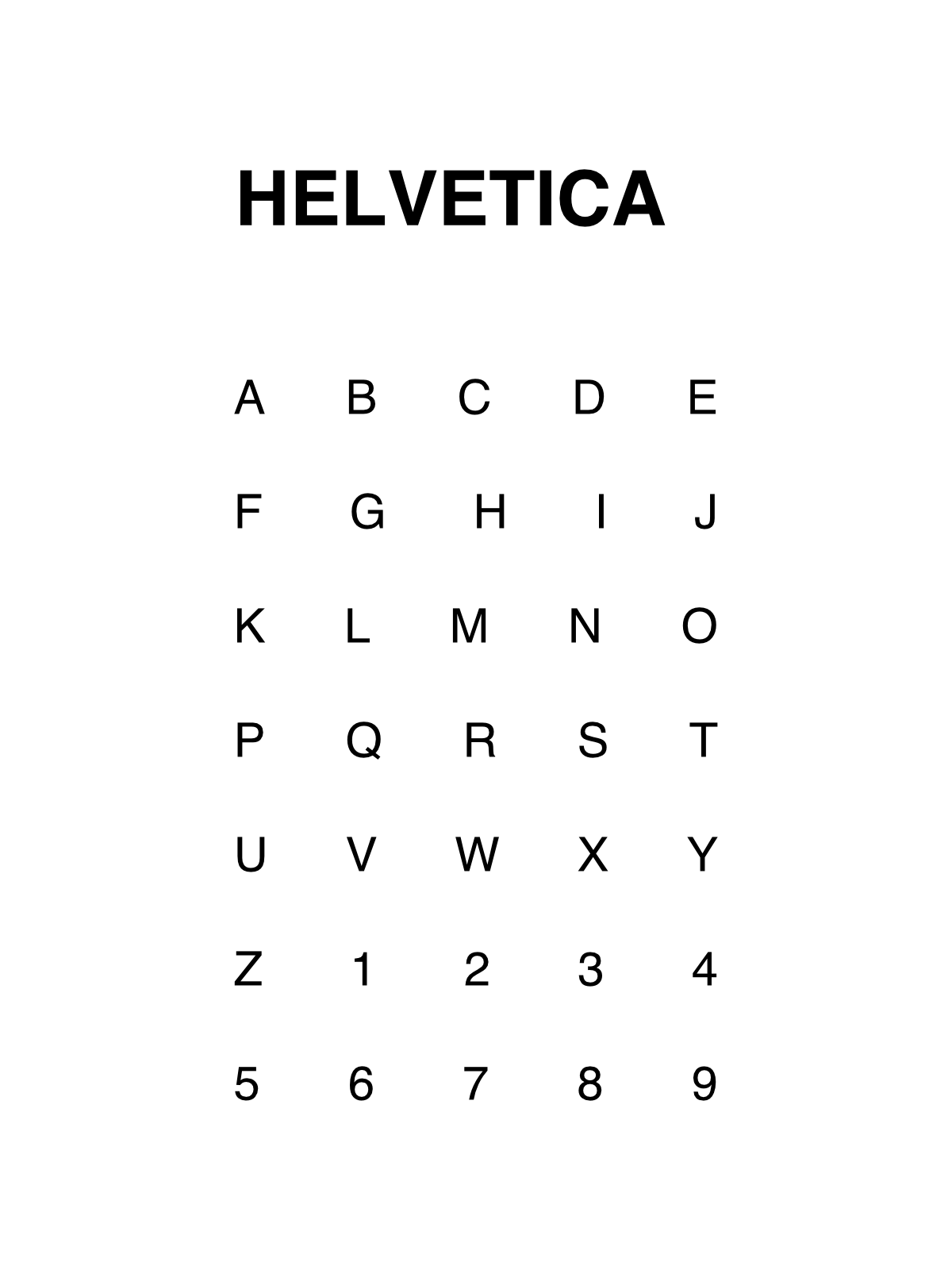
Impact
เป็นอีกหนึ่งฟอนต์ยอดนิยม เริ่มต้นพบเห็นใน Microsoft Windows ตั้งแต่ Windows 98 จนถึงปัจจุบันมันก็ยังไม่มีวันเชย
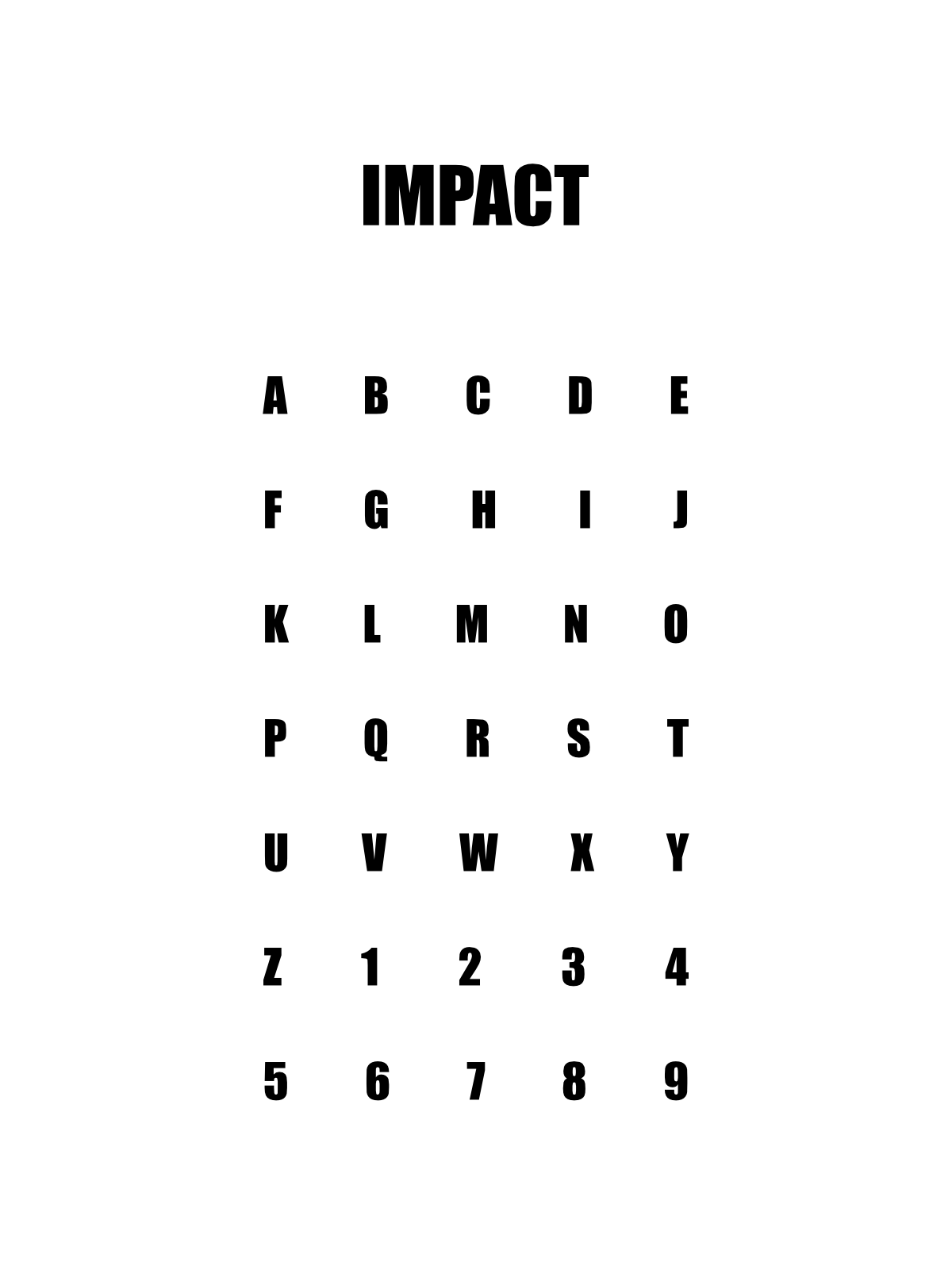
Arial unicode ms
ฟอนต์จากตระกูล Arial ที่มีการใช้กันเป็นมาตรฐานในอุตสาหกรรมเว็บไซต์ Arial unicode ms ส่วนใหญ่จะใช้เกี่ยวกับการเข้ารหัสภาษาคอมพิวเตอร์ ไม่แน่ใจในข้อมูลนัก ถือว่าเป็นฟอนต์ที่เรียบง่ายเหมาะกับการจัดวางในชุดตัวอักษรที่เยอะ
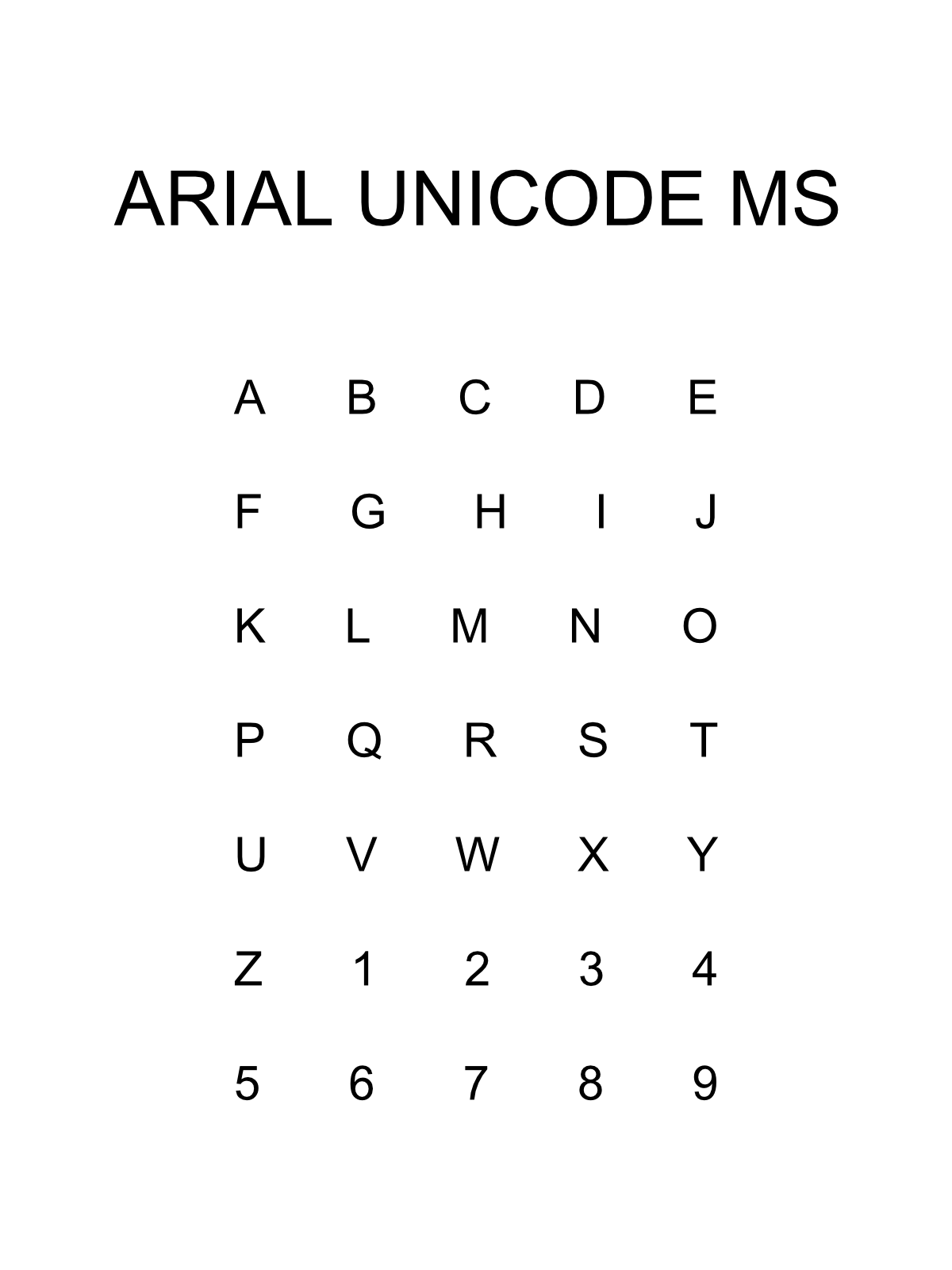
Baskerville
ถือกำเนิดช่วงปี 1750 ฟอนต์ที่มอบความรู้สึกจริงจัง คมชัด เป็นทางการ ส่วนมากถูกใช้กับวงการธุรกิจหรือสื่อหนังสือพิมพ์ ส่วนตัวเราเอาไปใช้กับบรีฟที่บอกว่า ขอหรู ๆ อยากดูแพง ส่วนใหญ่ได้ผล
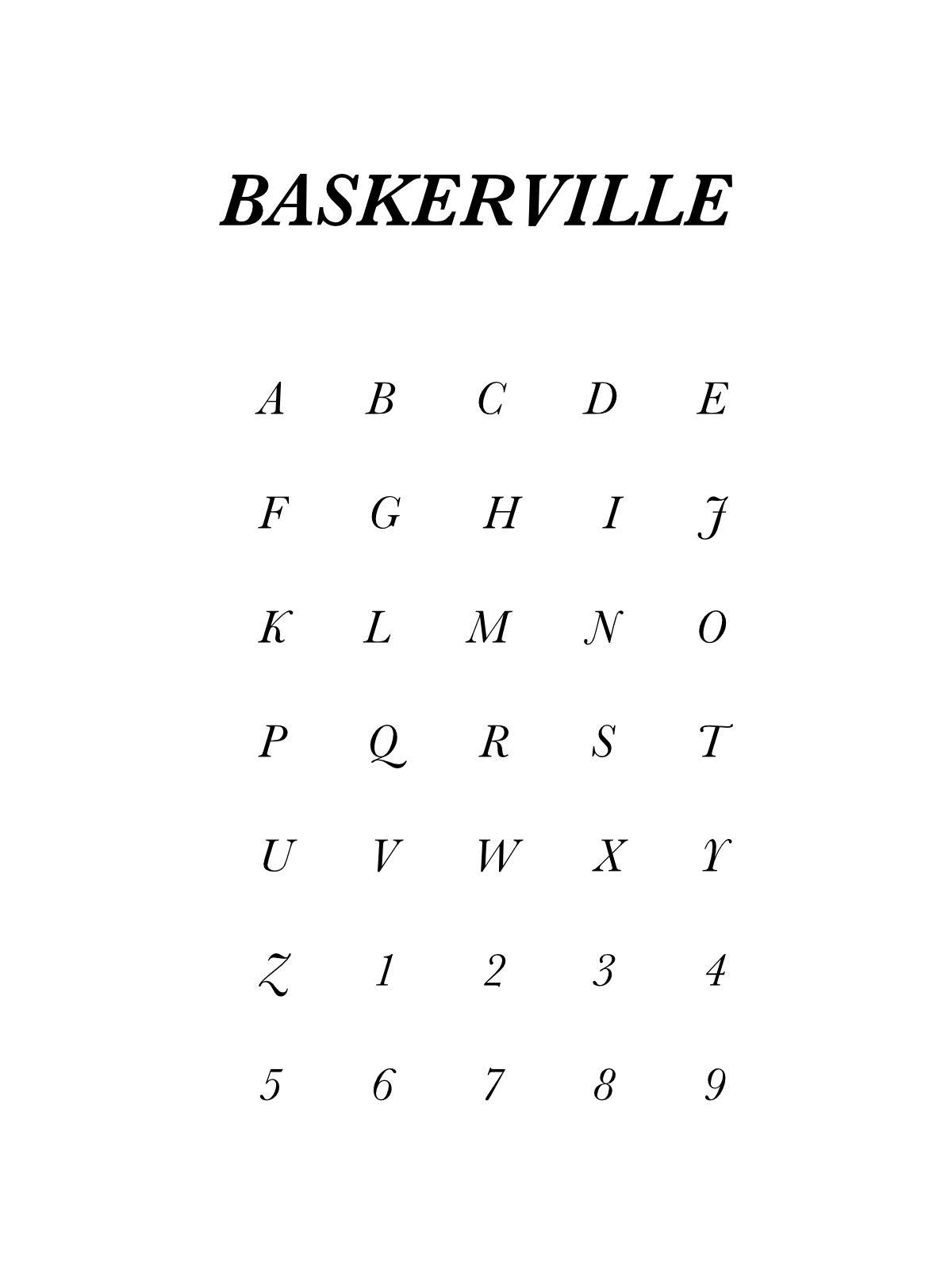
DIN alternate
หาข้อมูลไม่เจอมากนัก แต่เป็นฟอนต์ที่ชอบมากอีก 1 ตัวที่ติดมาในเครื่อง มันถูกปล่อยในปี 1995 จาก FontShop ที่เป็นผู้ผลิตฟอนต์รายใหญ่ในวงการ
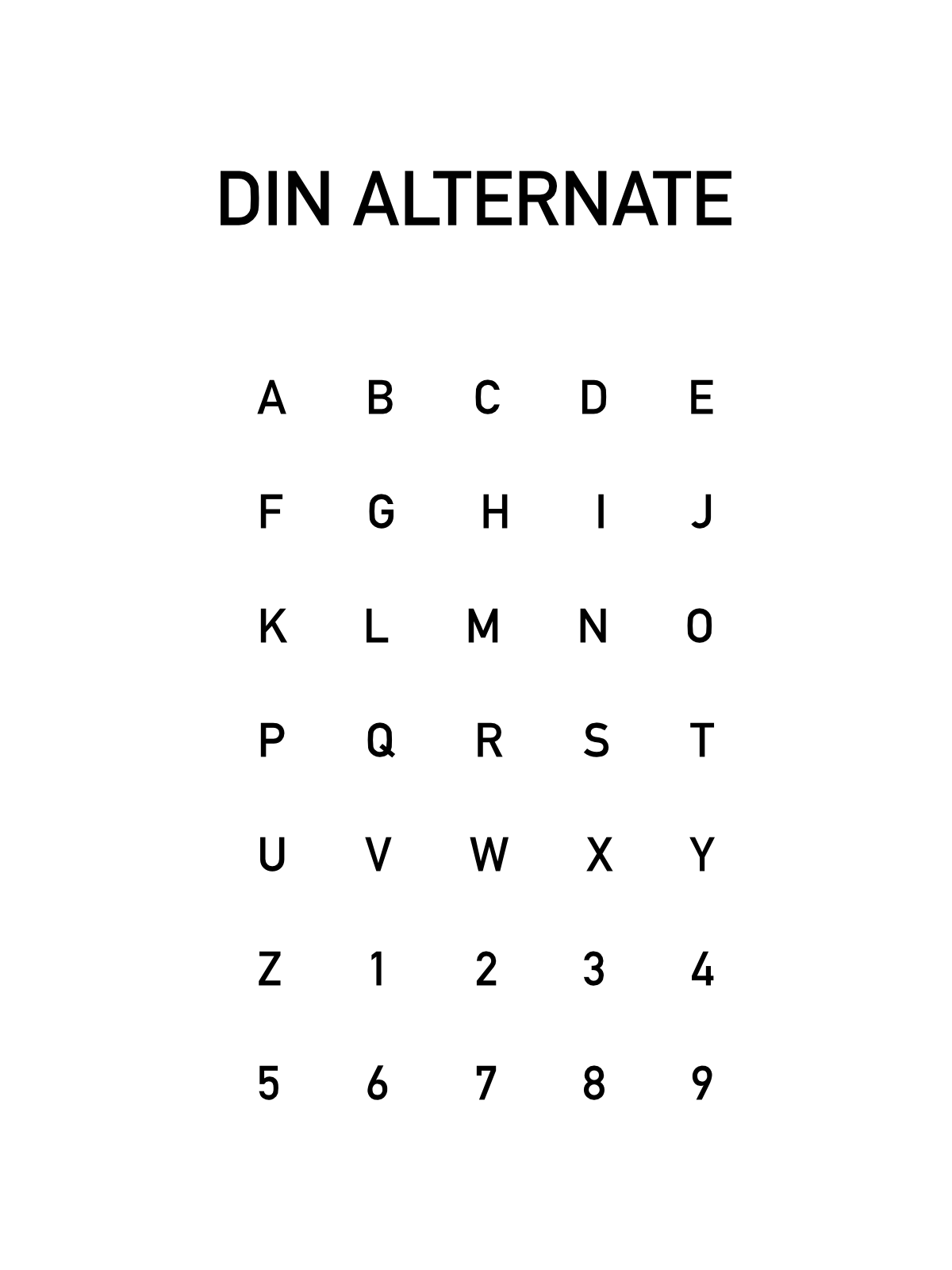
มันอาจจะไม่ได้เกิดปาฏิหาริย์ได้ทุกครั้ง เราก็ควรพยายามหาท่าไม้ตายใหม่ ๆ ไว้อย่างสม่ำเสมอ เมื่อวานจวนตัว ก็ขัดกระบวนท่าอื่นมาให้รู้สึกว่าเราไม่ได้หยุดพัฒนา
แต่ละคนก็มีท่าไม้ตายเป็นของตัวเอง เช่นเพื่อนของเราเหล่านี้ เขาจะมีไม้ตายกันเป็นฟอนต์อะไร เหตุผลที่เขาเลือกอาจจะทำให้คุณนำไปปรับใช้กับงานของตัวเองได้ในอนาคต
เลือกใช้ Sukhumvit Set เพราะมันมีความเรียบอ่านง่าย หน้าตาไม่แย่ ใช้ร่วมกับเลย์เอาท์อื่น ๆ สะดวก
เคยใช้ Font นี้ ในนิทรรศการของตัวเอง มันใช้ง่ายและดูดี มีน้ำหนักครบ ตัว Bold ก็แข็งแรง
หรือถ้าอยากทำเป็น Text ก็มี Regular ที่บางลงหน่อย สามารถเลือกใช้ได้ตามความเหมาะสมเลยค่ะ
ใช้ DB Adman แบบไม่มีเหตุผลรองรับ แค่มันคือตัวเลือกแรก ๆ และใช้มันบ่อยสุด
ทุกคนล้วนมีไม้ตายเป็นของตัวเอง แล้วไม้ตายของคุณละเป็นแบบไหนและหวังว่าฟอนต์ที่เราหยิบขึ้นมาแนะนำ จะเป็นประโยชน์ให้กับเพื่อน ๆ ไม่ทางใดก็ทางหนึ่ง